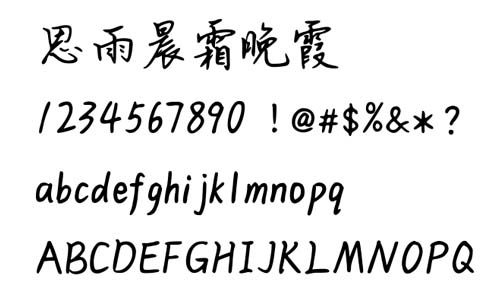
思雨晨霜晚霞是思雨字庫推出的一款非常漂亮的手寫藝術(shù)字體,晨霜映晚霞,清風(fēng)拂佳人。該字體是在國家標(biāo)準(zhǔn)簡體字庫GB2312所包含6763漢字的基礎(chǔ)上,又增加了近200常用字,已經(jīng)覆蓋了大陸99.75%的漢字使用頻率,足以滿足日常需求。歡迎喜歡思雨晨霜晚霞字體的朋友前來下載使用。